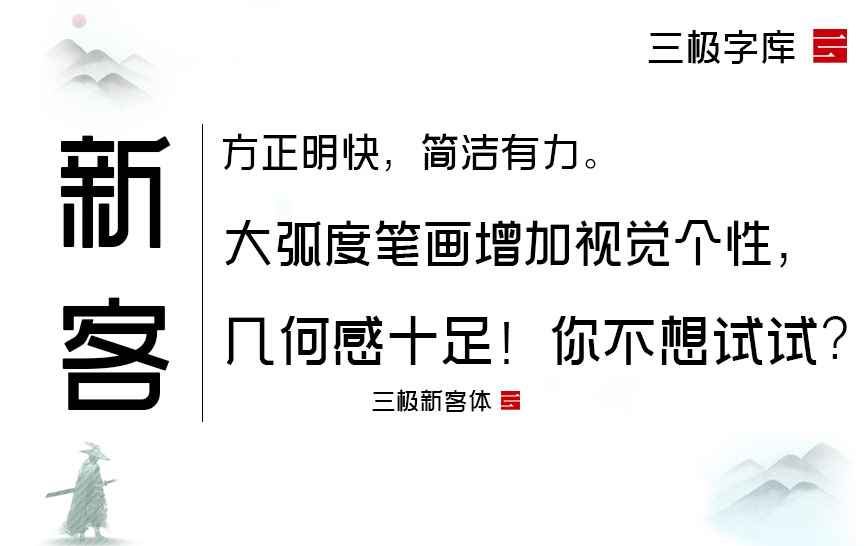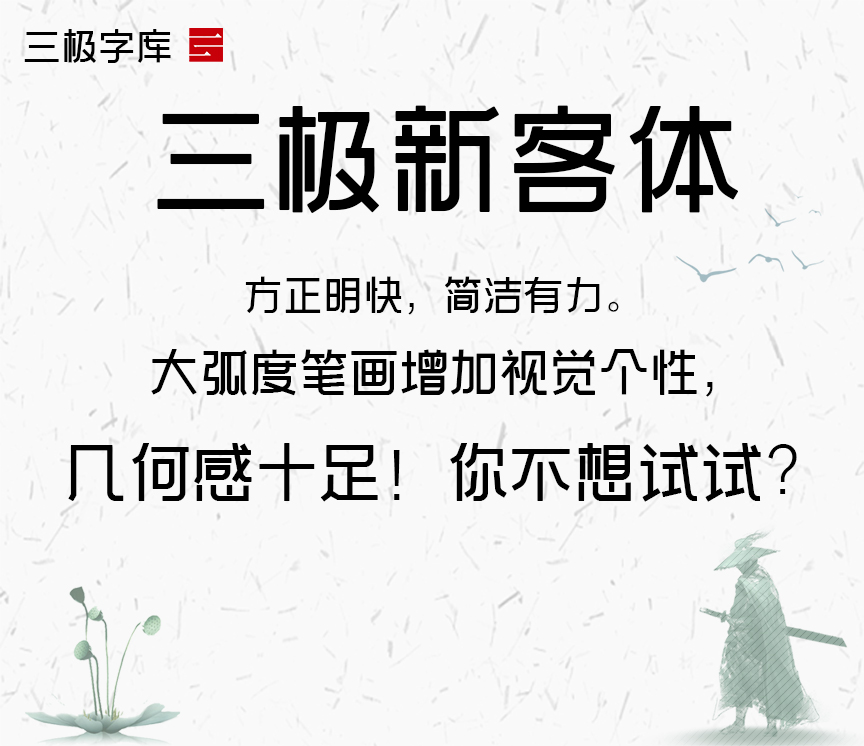
三极新客体是是一款几何感十足的创意字体。其笔画多以对称的手法来表现,撇、捺都有明显的几何转折,不同于书写状态的连续弧线。起笔收笔都为圆角,字体更加精致,使字体刚中带柔。使用了大弧度笔画加强了字体特有的视觉个性。字形方正明快,简洁有力,适用于书刊封面、广告品牌、产品包装设计及空间导视应用。
适用媒介:书籍、报纸、杂志、广告、标志、宣传册、包装、动漫、屏幕显示、交互设计。